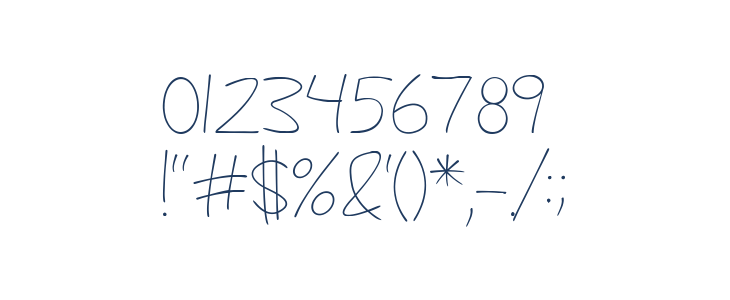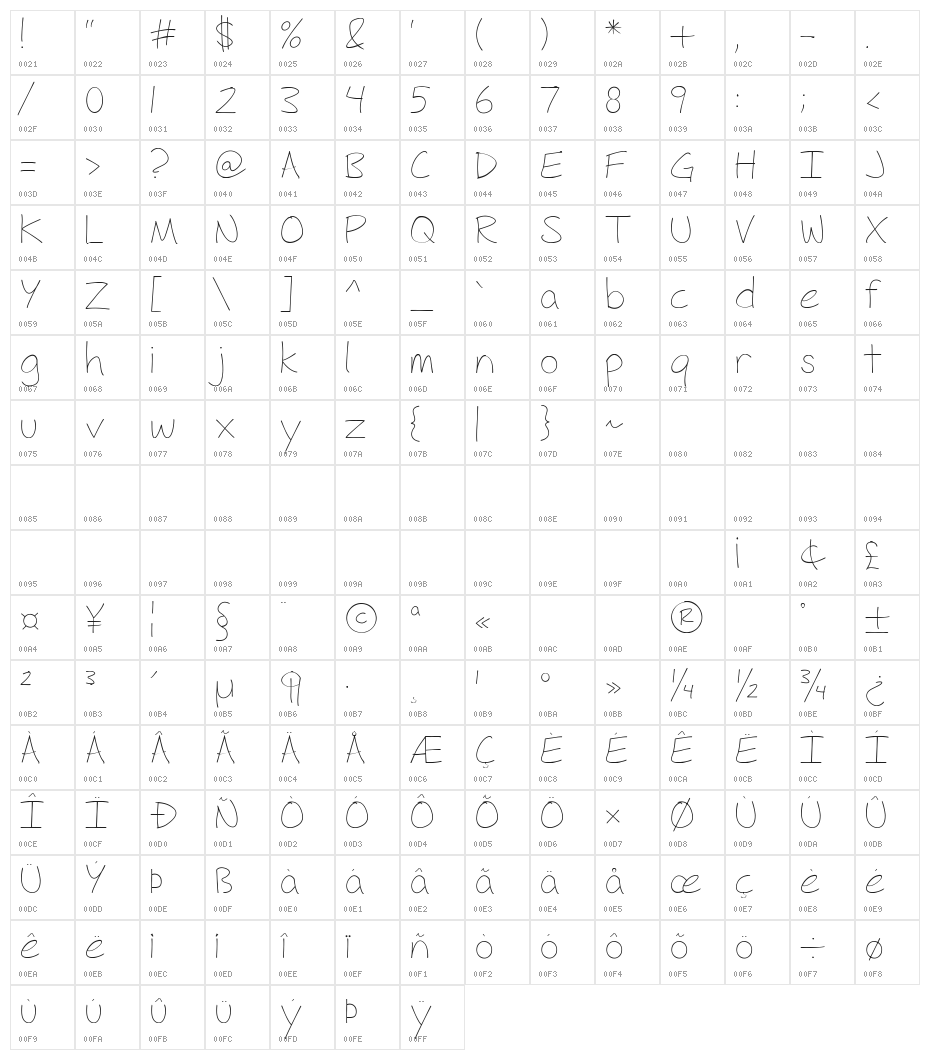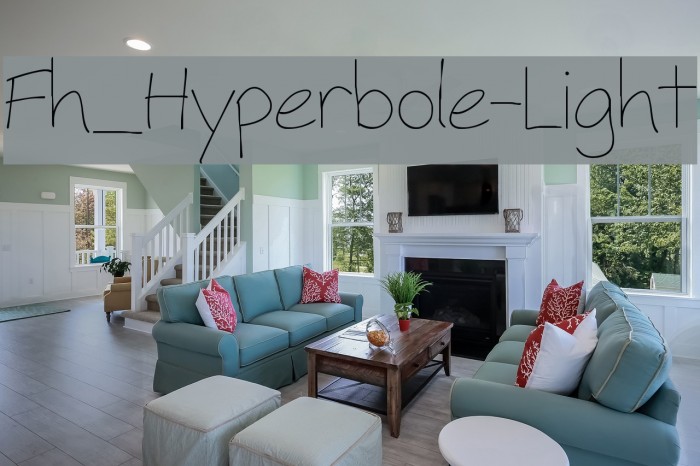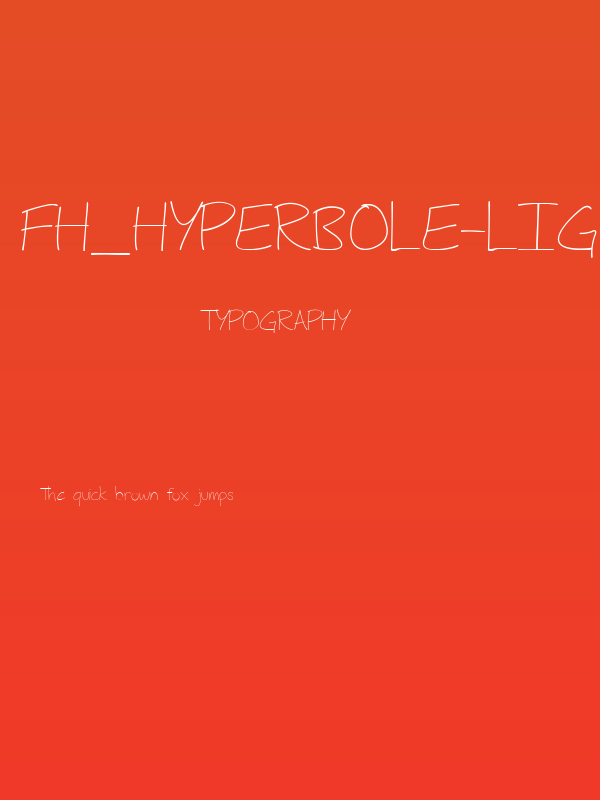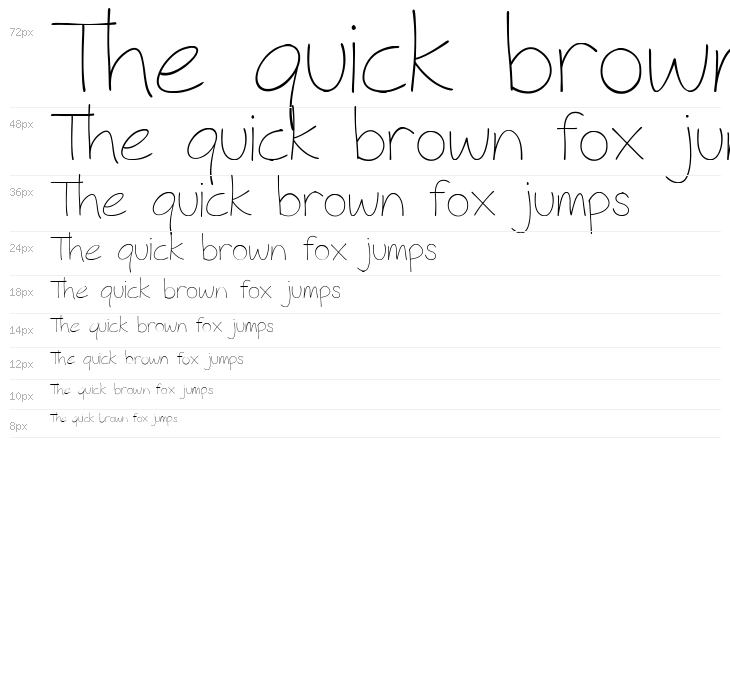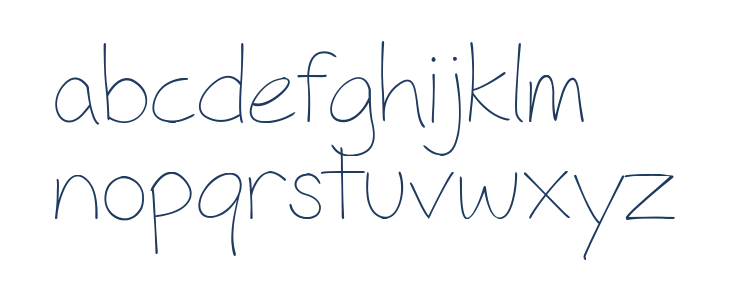
Fh_Hyperbole-Light Font
| Peso | Light |
| Stile generale | Casual |
| Caso d'uso | Logos, Headlines, Informal Text |
| Progetti proposti | Ideal for greeting cards, personal blogs, children's books, and casual branding. |